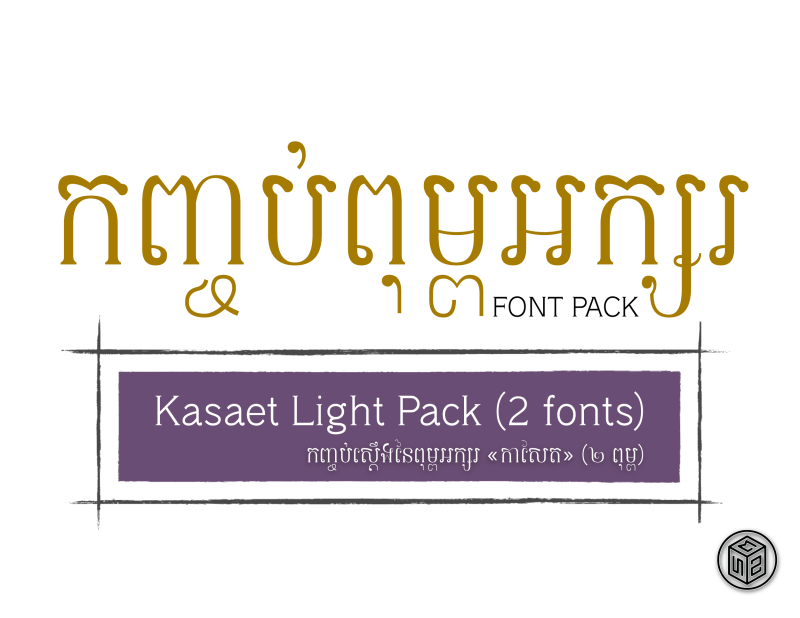
Kasaet [Pack] Light (2 fonts)
Mini-pack (2 fonts: Light and Light Italic) set for the Kasaet font family featuring classic serif style Aksar Chhor (Khmer) and Roman-Style Latin serif
Kasaet Light គឺជាពុម្ពអក្សរ Opentype ដែលប្រើបាននៅក្នុងផលិតផលសូហ្វវែរកុំព្យួទ័រជាច្រើនប្រភេទដែលគាំទ្រ OTFs។ ប្រើក្នុងការរចនាផលិតផល ផ្លាកយីហោ ឡូហ្គោ ក្រាហ្វិក ទីផ្សារ ឬគ្រប់ទីកន្លែងណាដែលអ្នកអាចបញ្ចូលភាសាខ្មែរ។ Kasaet ត្រូវបានបង្កើតឡើងដើម្បីផ្ដល់នូវការអានឲ្យងាយស្រួលក្នុងអត្ថបទវែង និងអត្ថបទបោះពុម្ពផ្សេងៗ។ សំណុំបែបបទធម្មតាគឺផ្អែកលើអក្សរឈរ។
ពុម្ពអក្សរនីមួយៗមានអក្ខរខ្មែរនិងឡាតាំង។
1. ស្ដើង
2. ទ្រេតស្ដើង
Kasaet Light is an Opentype font that can be used in a variety of computer software products that support OTFs. Use it in product designs, branding, logos, graphics, marketing, or anywhere you can type in Khmer. Kasaet was created to be easily read in long passages, such as newspapers and other print media.
Each font has the Khmer and Latin script.
1. Light
2. Light Italic